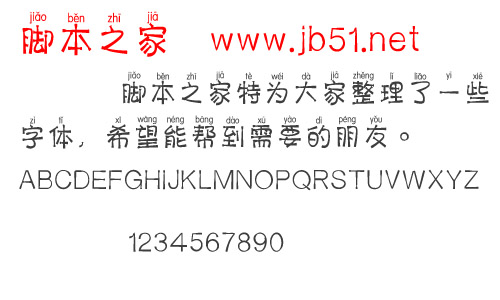
斑馬玉童拼音體字體是基于斑馬玉童體添加了拼音標注效果的一款中文藝術字體,該字體充滿童真活潑之氣,英文圓潤可愛,同時在漢字的上方有著對應的拼音和聲調,不僅讓文字更易發(fā)音,還擁有不一樣的視覺感,且字庫完整,可以很好的應用于文本裝潢、信息展示、網(wǎng)頁設計、篆刻制模、數(shù)據(jù)制作、裝潢設計、計算藝術設計、視覺設計、字帖等一切合法應用場景,有喜歡的朋友可免費下載收藏。